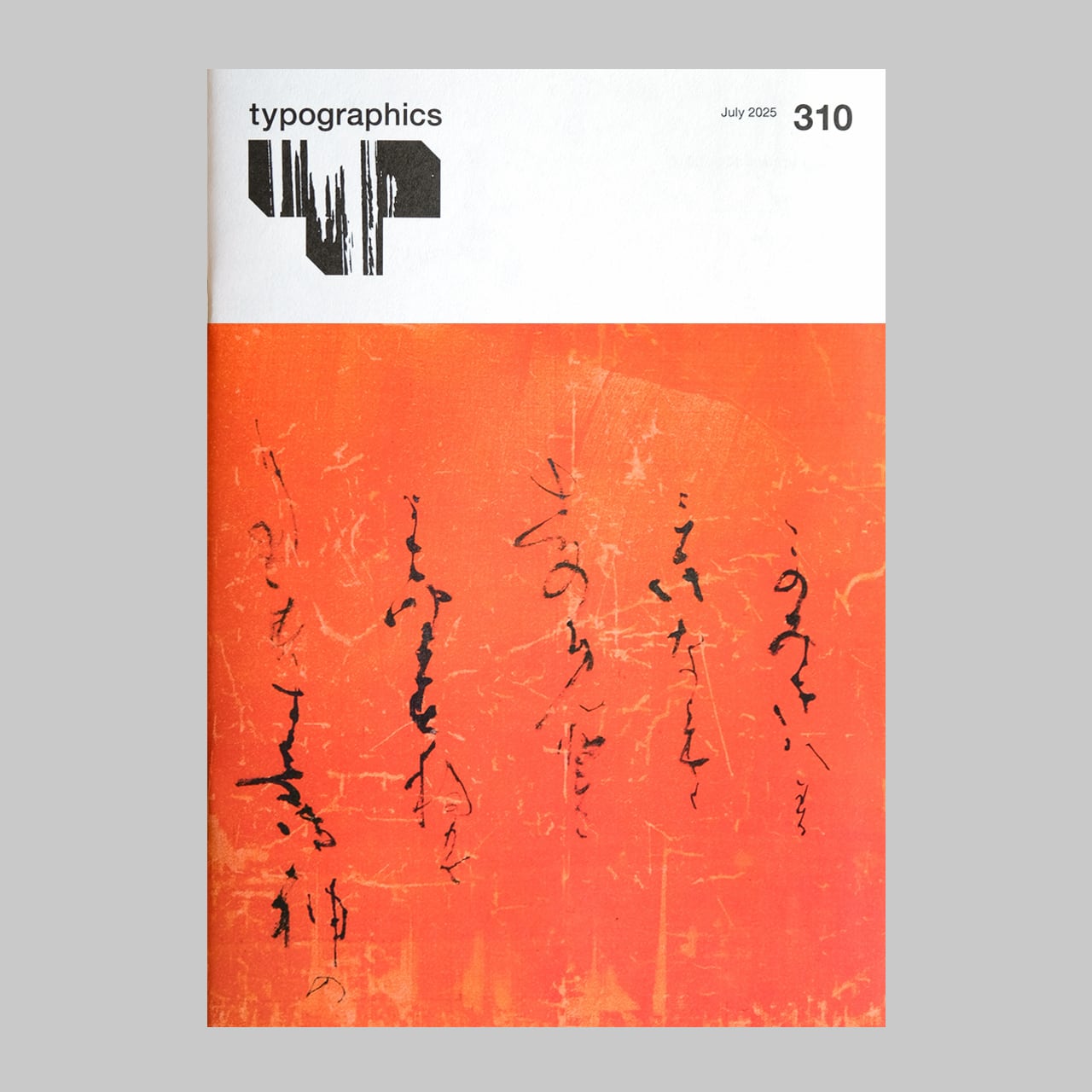
タイポグラフィックス・ティー/Typographics ti;
TEE誌は、創刊以来39年を越えデザイン関連協会が発行する出版物としては異例の長寿を誇ります。
各号の特集記事は、「日本の活字の歴史」といったアカデミックで堅い内容から、「公衆トイレのサイン」や「町中の看板」など私たちの日常に溢れる文字や記号まで、ありとあらゆる「タイポグラフィ」がテーマとなっています。
No. 310
[特集] 書家 井茂圭洞